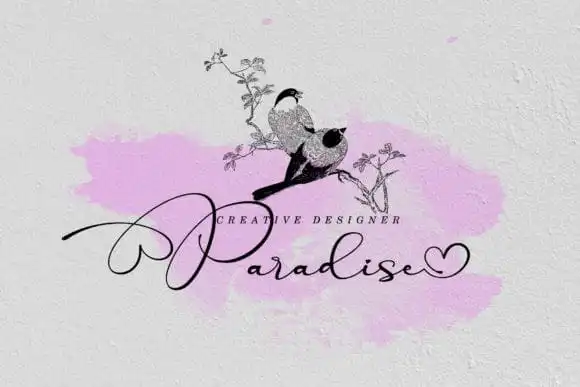
Parallove Calligraphy Font – Fonte Grátis
Parallove Calligraphy Font
A Parallove Calligraphy Font é uma nova e elegante tipografia script, criada para aqueles que buscam trazer um toque de romantismo moderno aos seus projetos. Suas linhas são finas, com base basilar variável e linha suave, o que a torna perfeita tanto para gráficos tradicionais quanto para as mais modernas aplicações digitais. Este estilo calligráfico abraça os sentimentos de amor em profundidade, criando uma experiência visual sofisticada e única. Ideal para quem busca algo romântico e contemporâneo em seus designs ou marcas da marca, esta fonte é perfeita para vários usos como cabeçalhos, cartões de convite, assinaturas, logotipos, identidades visuais, camisetas, folhas de carta, sinais, rótulos, cartazes e brochuras. A Parallove Calligraphy Font é uma escolha perfeita para designers buscando expressar sentimentos apaixonados de maneira moderna e inovadora.